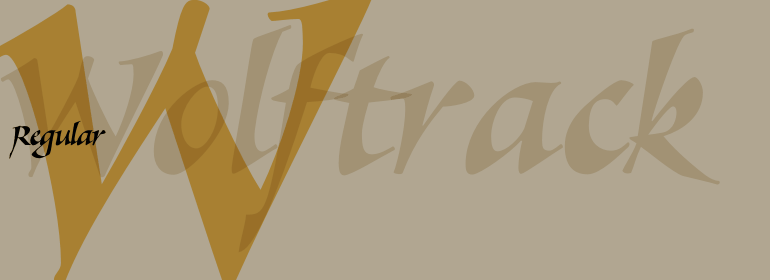
Wolftrack™
Wolftrack™,这款字体结构工整、笔画清晰,兼顾美观与易读性,适用于标题、正文、海报、包装、LOGO 等多种场景。字形优雅稳定,风格百搭耐看,适配日常排版与创意设计,让文字呈现更舒适、更具质感。Wolftrack™一笔一画,皆是细节,以均衡的比例、流畅的线条打造舒适视觉体验,字形端正大气,风格简约现代。无论是商业设计、品牌宣传还是日常排版,都能轻松驾驭,让文字更有格调与力量。Wolftrack™字体下载。